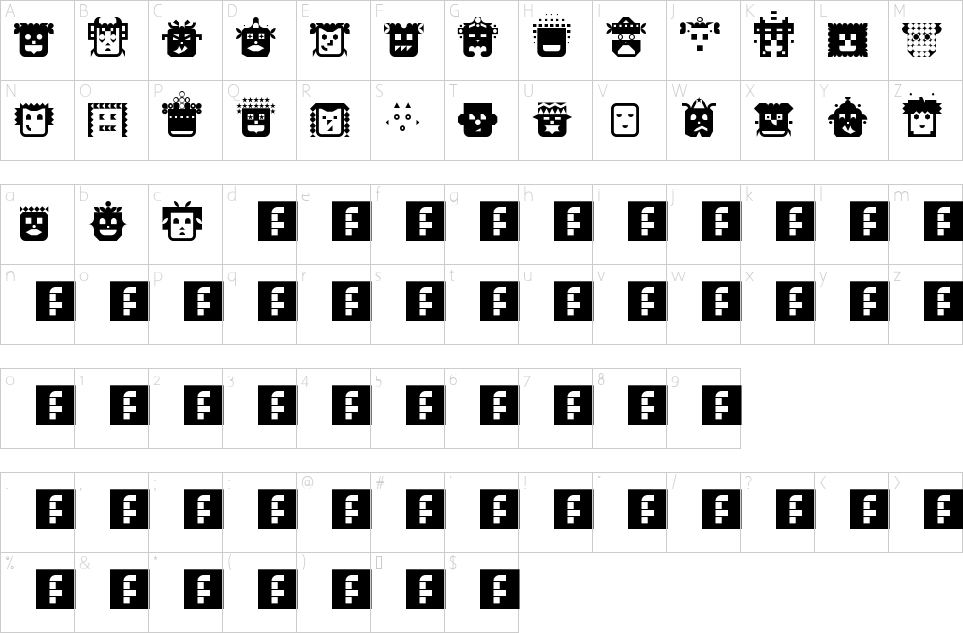
A fonte People Diverse é uma escolha perfeita para quem busca diversidade e criatividade em suas criações digitais. Desenvolvida por Adien Gunarta, esta fonte oferece uma gama de estilos variados e vibrantes, garantindo um toque único a qualquer texto ou design. Com 1,339 downloads desde sua disponibilização, é evidente que a comunidade de designers está encantada com a personalidade única dessa fonte. Não apenas adequada para projetos em Windows e Mac, People Diverse é uma fonte gratuita que se destaca por sua variedade e facilidade de uso. Para aqueles que buscam diversidade na linguagem visual, esta fonte é uma ótima opção.